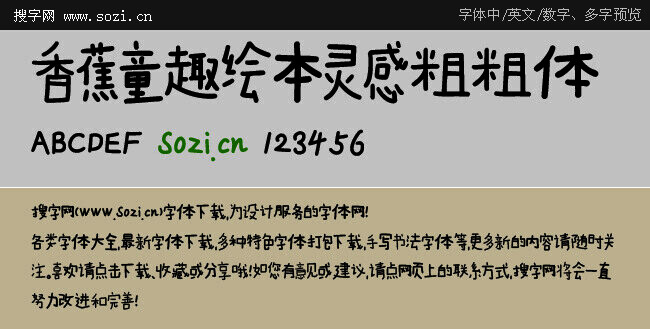
香蕉童趣繪本靈感粗粗體
搜字網(wǎng)提供一款香蕉童趣繪本靈感粗粗體中文藝術(shù)字體下載,香蕉童趣繪本靈感粗粗體是一款卡通藝術(shù)字體,香蕉童趣繪本靈感粗粗體打破原有的結(jié)構(gòu)順序,以兒童視角對(duì)本款字體進(jìn)行手繪書寫,結(jié)構(gòu)穿插的變化無序正如兒童們的想法,天馬行空,充滿童趣。適合包裝設(shè)計(jì)、海報(bào)設(shè)計(jì)、廣告設(shè)計(jì)等應(yīng)用。